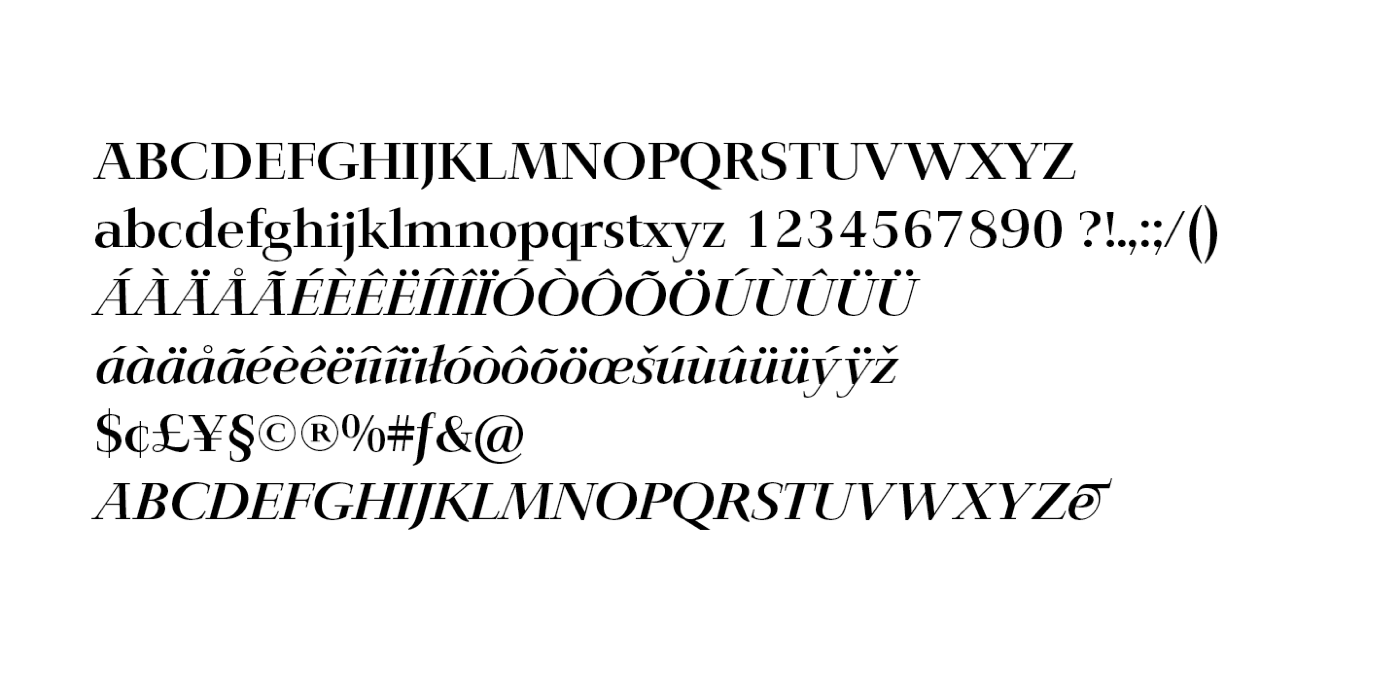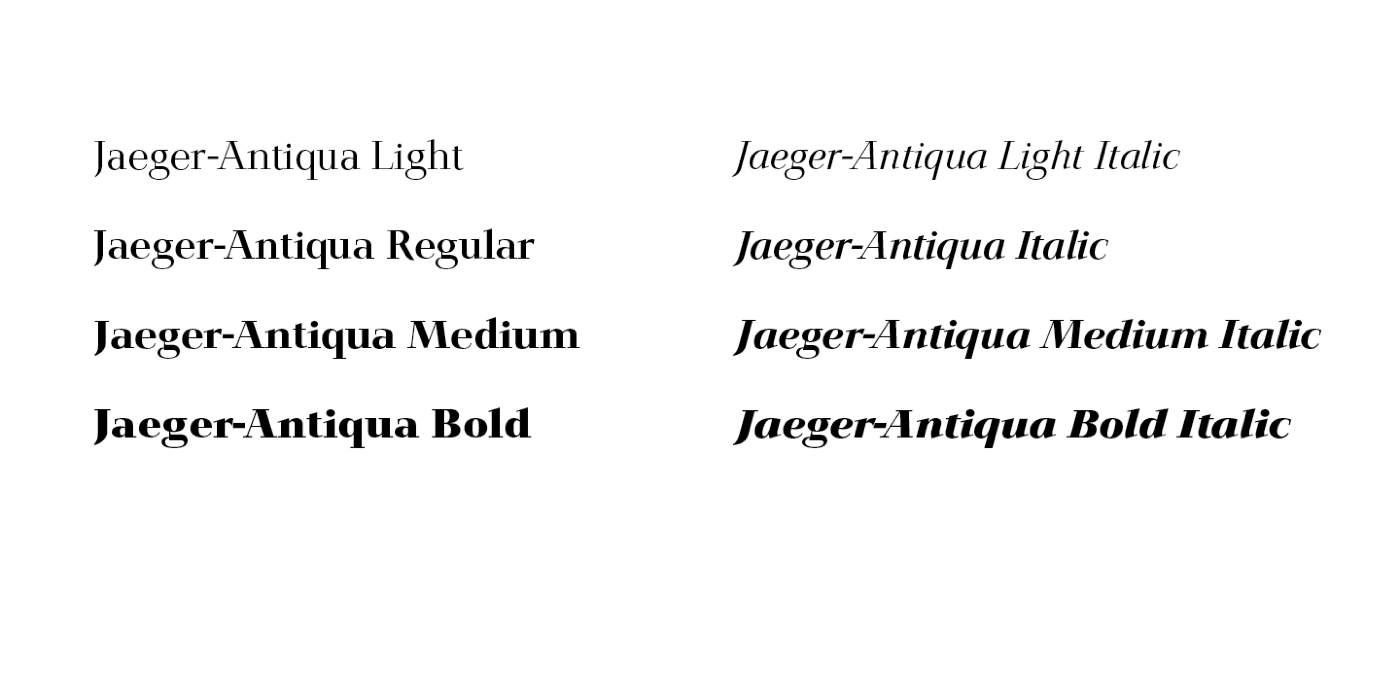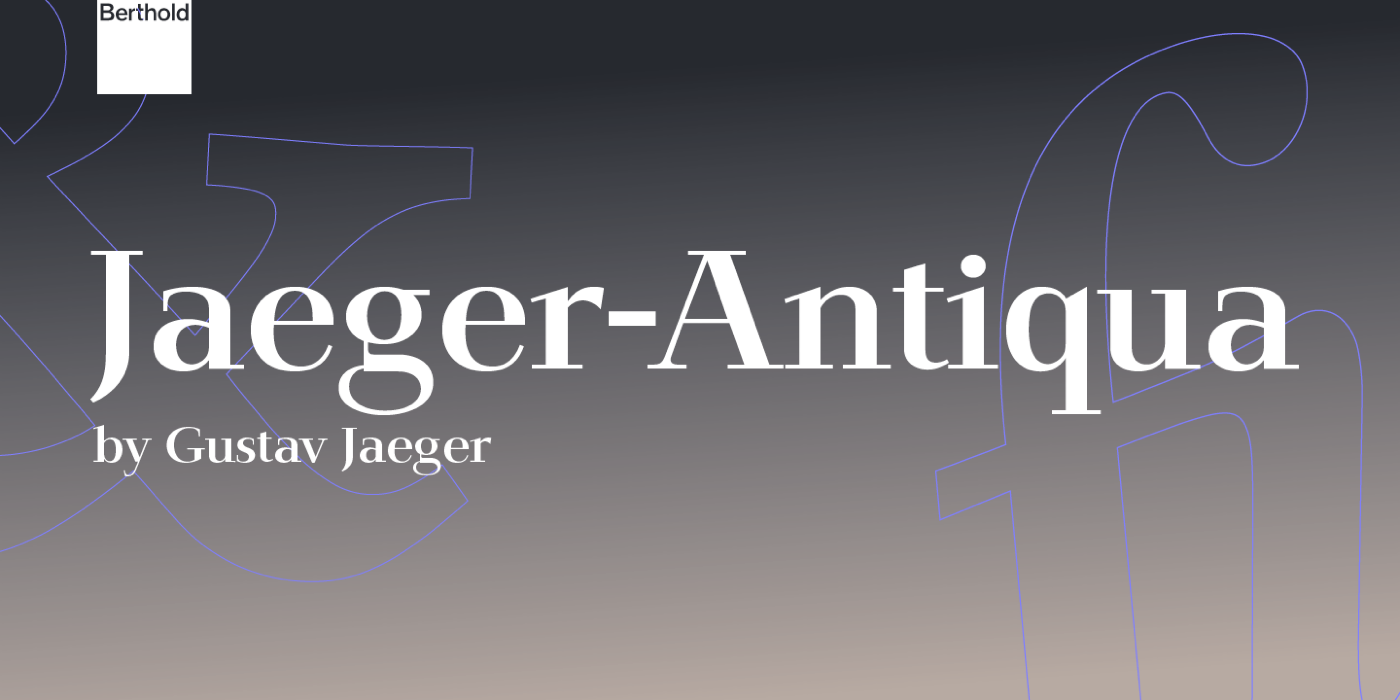
Font-Wiki: Jaeger-Antiqua
Die Jaeger-Antiqua ist eine Schriftfamilie mit klassizistischem Duktus und erschien in den 1980er-Jahren als Fotosatzschrift bei der H. Berthold AG. Die vier Strichstärken mit Kursiven sind heute mit westeuropäischer Zeichenbelegung über Monotype verfügbar.